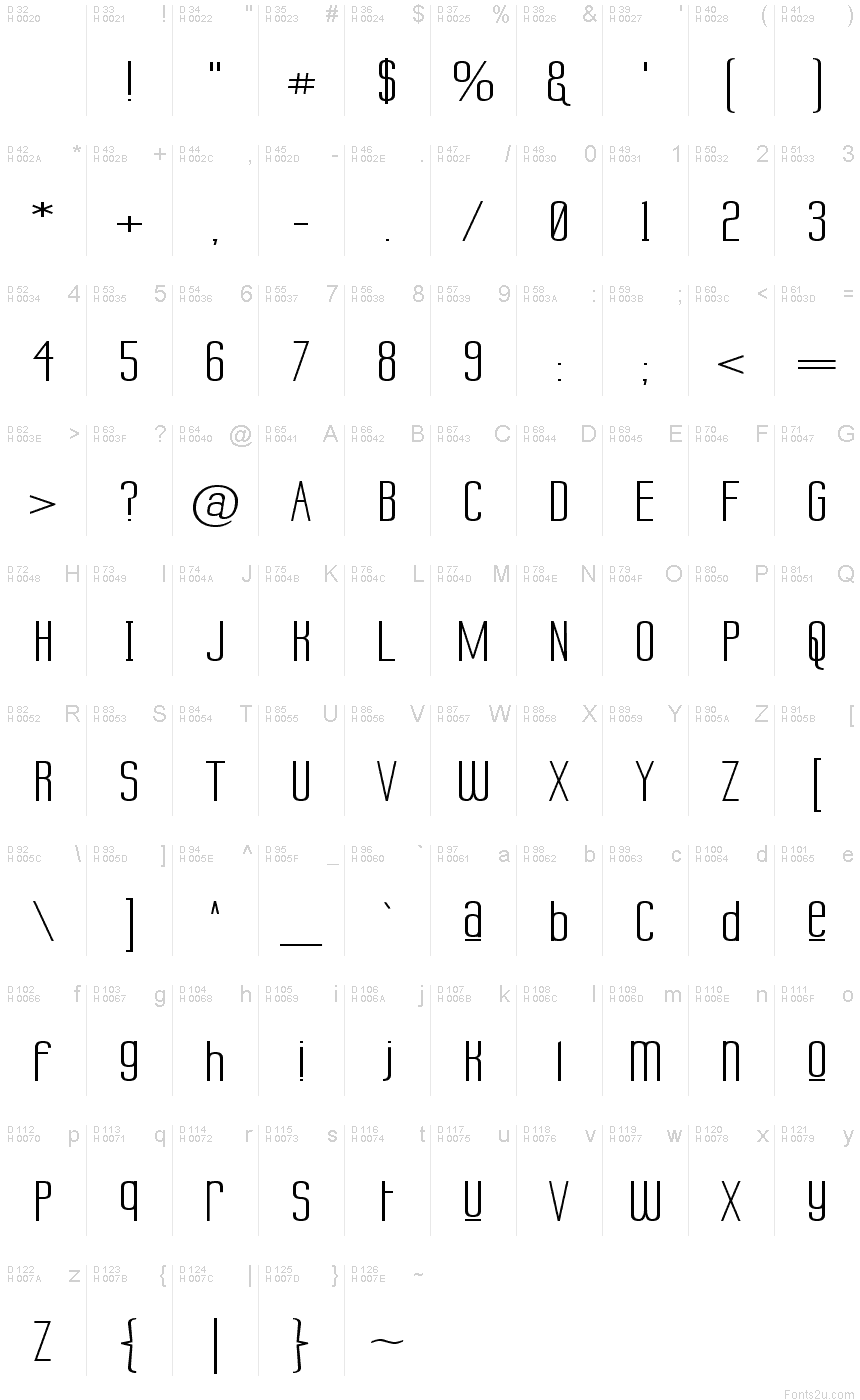
Labtop Unicase Upper Wide
Labtop Unicase Upper Wide autorstwa Graham Meade i Apostrophic Labs to darmowy, utrzymany w stylu retro font typu display. Wyróżnia się wysokimi, wyprostowanymi formami i zaokrąglonymi, prostokątnymi krzywiznami, dzięki którym litery sprawiają wrażenie wąskich, gładkich i lekko technicznych. Powtarzalna sylwetka nadaje projektowi wyrazisty, niemal szyldowy rytm, balansujący między geometrycznym bezszeryfem a wczesnym brandingiem elektronicznym.
Font świetnie sprawdza się na okładkach płyt, szyldach, tytułach plakatów, opakowaniach i nagłówkach stron internetowych, gdzie krótkie linie pozwalają w pełni wykorzystać jego pionowy charakter. Ponieważ kształty pozostają proste i monolinijne, a zaokrąglone rogi łagodzą geometrię, font doskonale sprawdzi się w grafikach technologicznych czy projektach inspirowanych stylem połowy wieku, nie sprawiając przy tym wrażenia surowego.